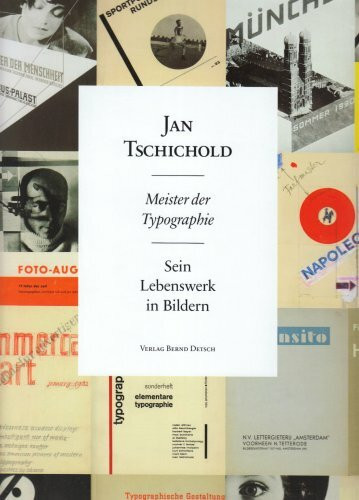
Jan Tschichold. Meister der Typografie
"Jan Tschichold. Meister der Typografie" von Cees de Jong ist eine umfassende Darstellung des Lebens und Wirkens von Jan Tschichold, einem der einflussreichsten Typografen des 20. Jahrhunderts. Das Buch beleuchtet Tschicholds Werdegang von seinen frühen Jahren in Leipzig über seine prägenden Erfahrungen mit der Bauhaus-Bewegung bis hin zu seiner Arbeit in der Schweiz und Großbritannien. Es wird detailliert auf seine bahnbrechenden Ideen zur modernen Typografie eingegangen, die er unter anderem in seinem berühmten Werk "Die neue Typographie" formulierte. Zudem werden seine späteren Arbeiten für Penguin Books betrachtet, wo er das klassische Buchdesign revolutionierte. Das Buch enthält zahlreiche Abbildungen und Analysen seiner Arbeiten, die seinen Einfluss auf das Grafikdesign bis heute verdeutlichen.